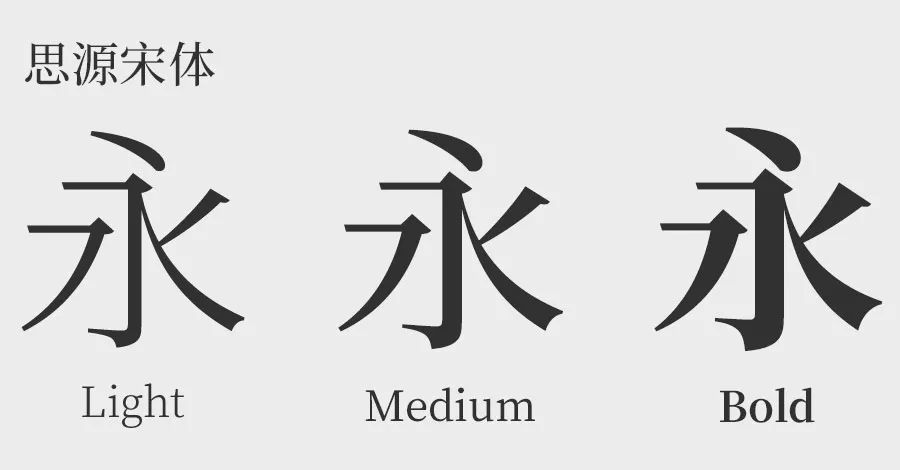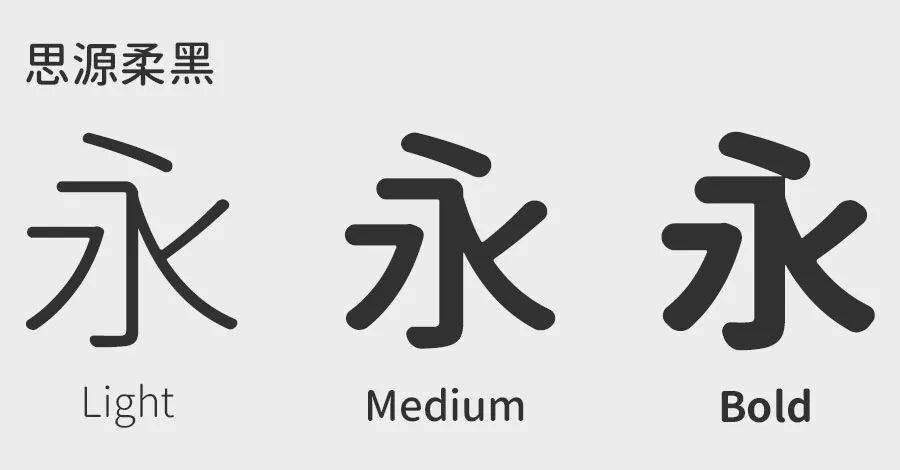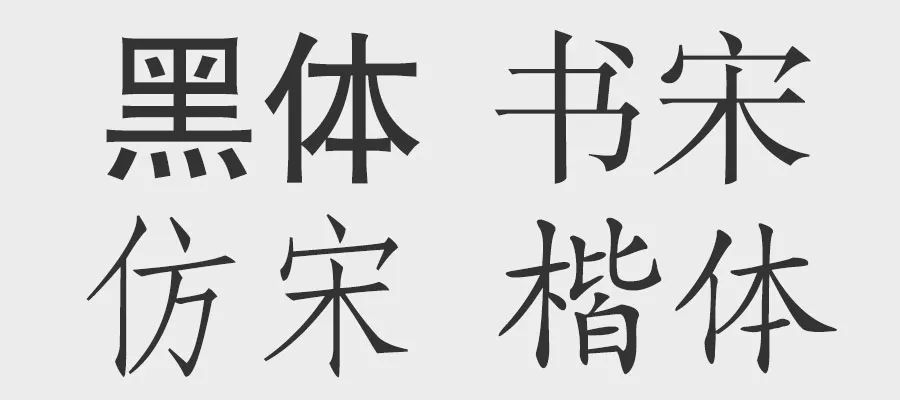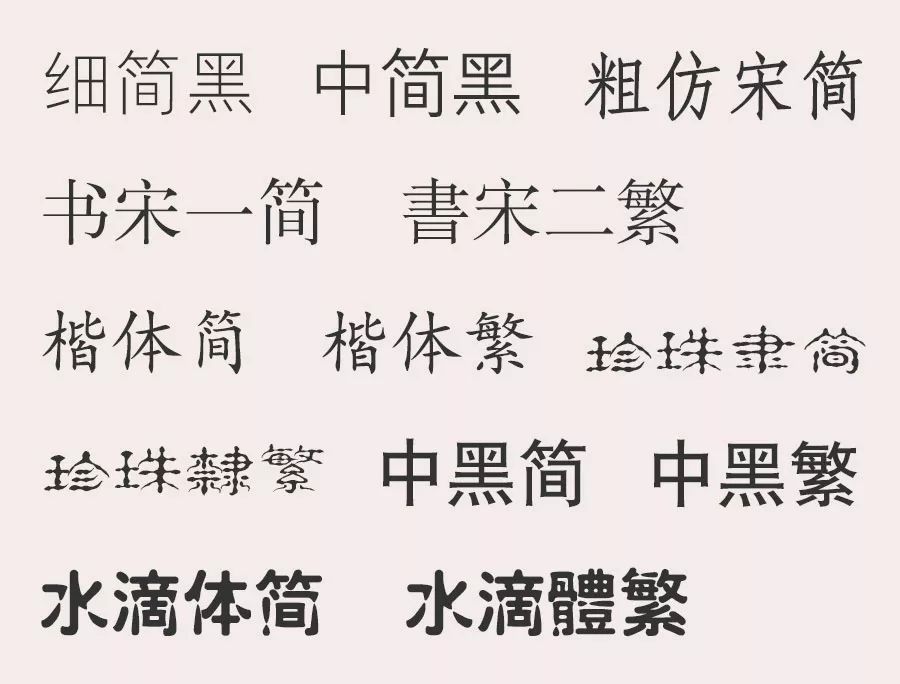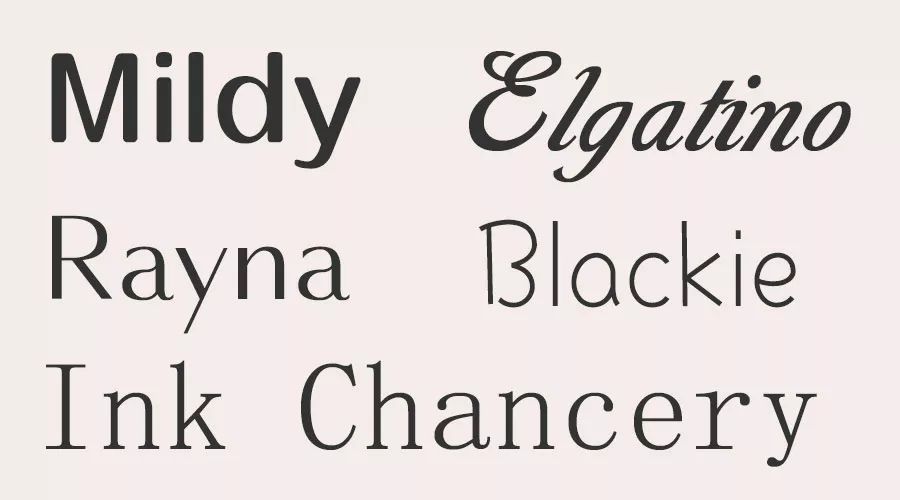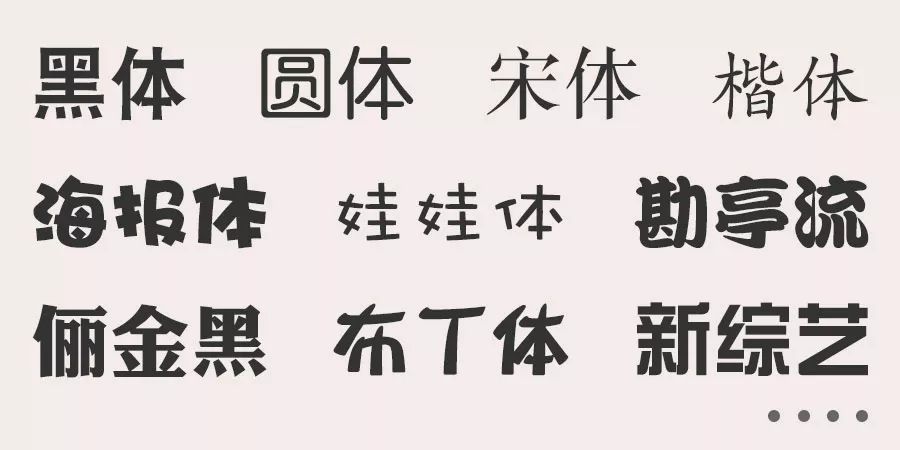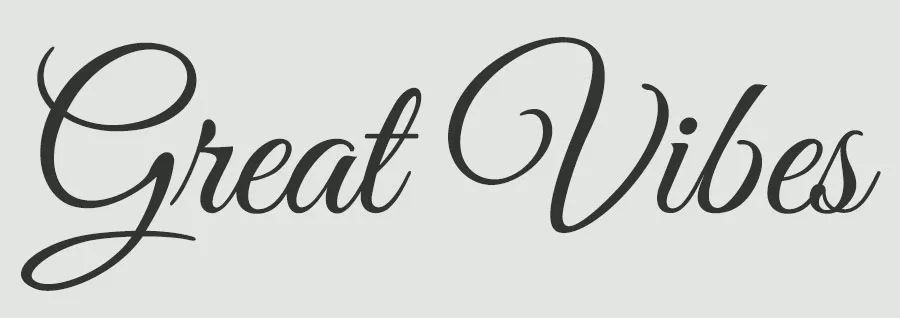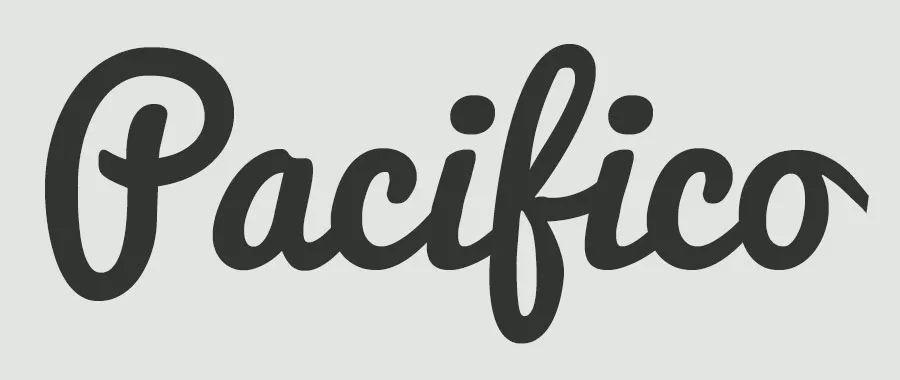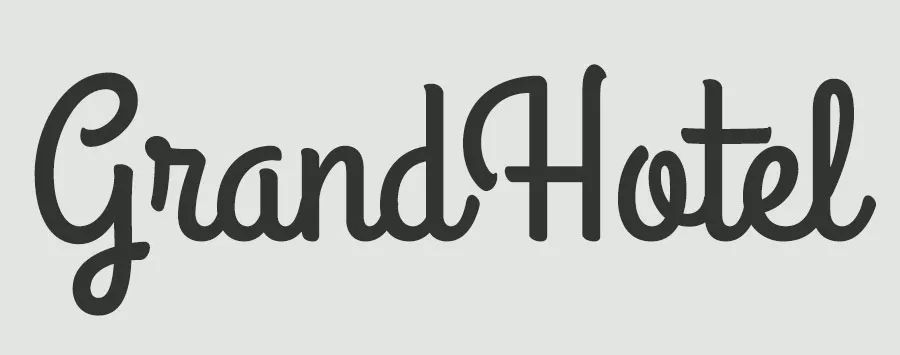
坐拥百款免费字,从此不惧律师函!
这些都是免免免免免免免免免免免费的@字由
进入正题~小编为大家整理了一套可以免费商用的字体
标题类
01
郑庆科黄油体
可爱的“黄油体”适用于店招、banner、标志等领域。
02
濑户字体SetoFont
濑户字型是日本的一位业余字体设计师的个人手书
丝毫不造作,天然呆自然萌,相信你会喜欢
03
庞门正道标题体
庞门正道阿门发起的公益项目
字形比较扁平、圆滑,设计的可塑性很强
是一款适合用作海报、H5的标题字
04
站酷系列
站酷高端黑 | 站酷快乐体 | 站酷酷黑体 | ZCOOL Addict Italic
正文字
01
思源系列
思源宋体 | 思源黑体 | 思源柔黑
思源黑体
Adobe 与 Google 协力推出,西塚凉子主导设计
汉字部分基于小塚黑体设计
西文部分采用 Source Sans
完整支持简体与繁体中文以及日文、韩文
七种字重,每一种字重包括 65535 个字形
思源宋体
思源宋体是对应于思源黑体的宋体字体
同思源黑体一样,是为了响应统一设计的需求
以服务于东亚 15 亿人口而推出的免费可商用字体
思源柔黑
思源柔黑体是基于思源黑体修改而成的圆体版思源字体
作者是日本的自家製フォント工房。
02
花园明朝体
花园明朝体主要是以旧字型为主,收录了所有的汉字和日文假名
实现了Unicode 全汉字收录,非常的自由开放
03
方正字库
方正黑体 | 方正书宋 | 方正仿宋 | 方正楷体
贴心的小编就给大家介绍几款免费电商专用字体
电商系列
01
汉仪字库-京东
中文字库
汉仪细简黑简 | 汉仪中简黑简 | 汉仪粗仿宋简
汉仪书宋一简 | 汉仪书宋二繁
汉仪楷体(简/繁) | 汉仪珍珠隶(简/繁)
汉仪中黑(简/繁) | 汉仪水滴体(简/繁)
西文字库
Mildy | Elgatino | Rayna | Blackie | Ink Chancery
02
华康字体
华康黑体 | 华康圆体 | 华康宋体
华康海报体 | 华康娃娃体 | 华康勘亭流 等
我们这么fashion当然要经常用到西文
最后给大家介绍几款免费商用的西文字库
西文系列
01
TypeSETit
Great Vibes | Alex Brush
02
Vernon Adams
Pacifico
03
The League of MoveableType
Raleway | ChunkFive
Raleway 为家族字体,包含18款字型,共9个字重
04
Astigmatic
GrandHotel
05
Nick'sFonts
SeasideResort
06
IBM
IBM发布了首套自主设计的字体 IBM Plex
它将全面代替IBM原来使用的 Helvetica,成为IBM产品、网站、引导标识等通用字体
IBMPlex Family 由三大字体类型组成
Sans(无衬线体)
Serif(衬线体)
Mono(等宽字体)
每种类别有8种不同的字重